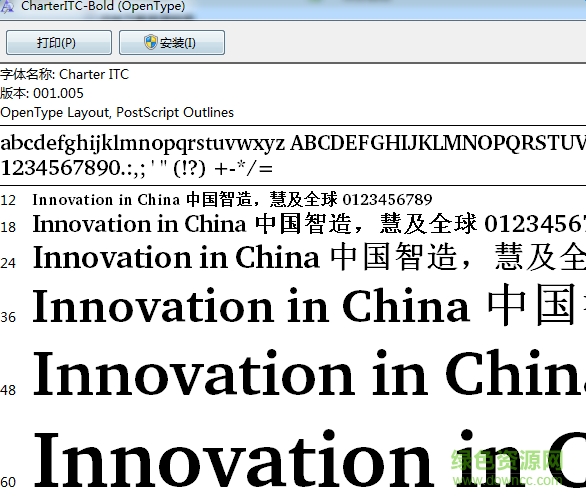
charter-bold字體是一款粗體英文字體,字型干凈易讀,不論是用來排版還是用于包裝設(shè)計(jì)等方面都很和諧,非常百搭的襯線字體,字型搭配歡迎大家免費(fèi)下載!
【文字分析】:了解字體的結(jié)構(gòu)和字體的特性,是我們排版優(yōu)秀的字體的依據(jù)。
字體排版設(shè)計(jì)中,點(diǎn)線面結(jié)合成的設(shè)計(jì)群體,高低錯(cuò)落、疏密聚散,是構(gòu)成形式美的重要因素。26個(gè)英文字母,根據(jù)字體的粗細(xì)設(shè)定節(jié)點(diǎn)組合,每個(gè)單獨(dú)的字母就構(gòu)成了音符。
【文字的韻律】:優(yōu)秀的字體排版,具有其獨(dú)特的美。由文字的律動(dòng)演繹出米美妙的音樂。
一段文案,不采用任何修飾與變化,字體字號(hào)顏色都不變,所產(chǎn)生的節(jié)奏是就是單詞與單詞之間的間隔,字體是唯一能體現(xiàn)情感的依據(jù)。